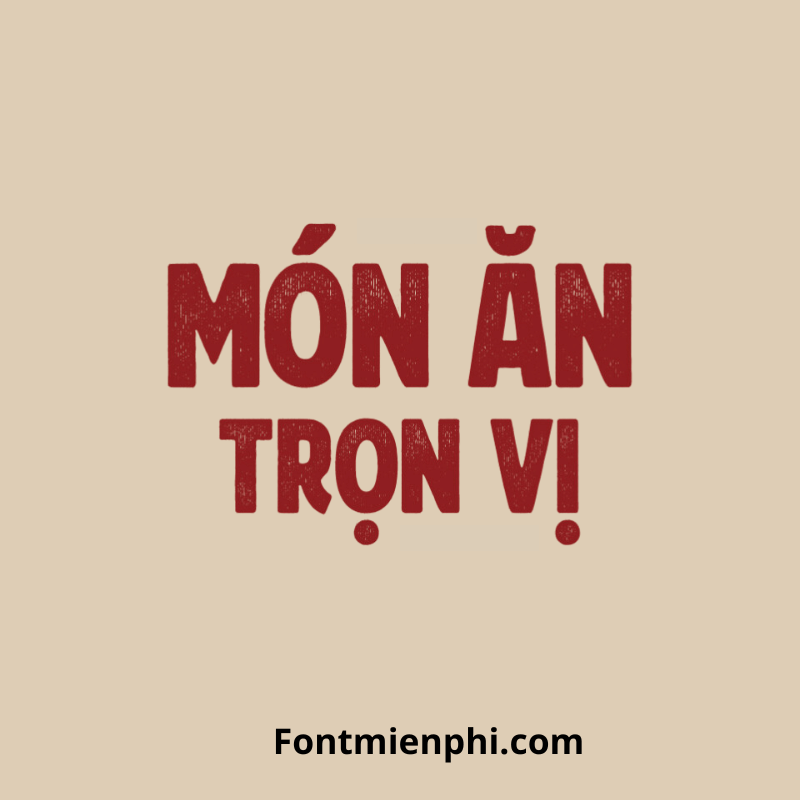
Font Việt hóa 1FTV VIP Rushford Printed
Font Việt Hóa 1FTV VIP Rushford Printed – Nét Chữ Độc Đáo, Sáng Tạo
Giới thiệu:
Font Việt hóa 1FTV VIP Rushford Printed là một trong những font chữ nghệ thuật được ưa chuộng nhất hiện nay, với thiết kế độc đáo và khả năng tương thích tiếng Việt hoàn hảo. Với phong cách in đậm, sắc nét, Rushford Printed phù hợp cho thiết kế poster, bìa sách, logo và các ấn phẩm sáng tạo khác.
Đặc điểm nổi bật:
• Thiết kế ấn tượng: Nét chữ được cách điệu với hiệu ứng in đậm, tạo điểm nhấn mạnh mẽ cho thiết kế.
• Hỗ trợ tiếng Việt: Font được Việt hóa đầy đủ, đảm bảo hiển thị rõ ràng các ký tự có dấu.
• Đa dạng ứng dụng: Phù hợp với nhiều dự án như quảng cáo, thời trang, nghệ thuật và đồ họa.
• Phù hợp với nhiều phong cách, từ cổ điển đến hiện đại.
Kết luận: